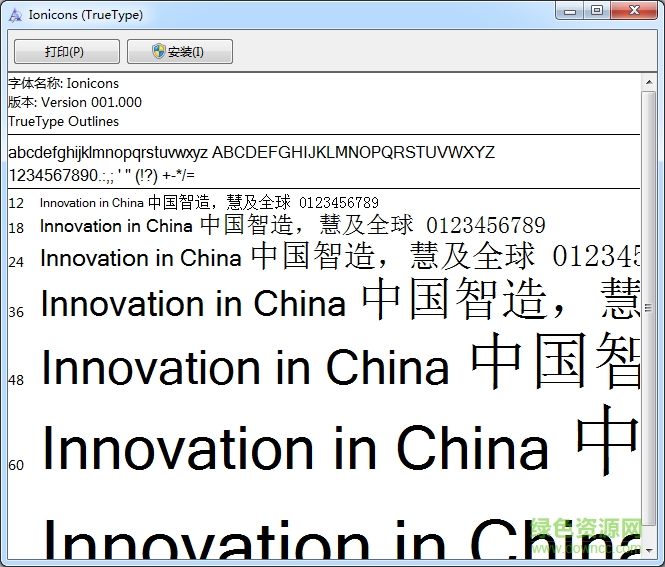
ionicons.ttf是系統(tǒng)軟件默認的一款字體,字形干凈簡練,有著端正的造型和大方的格調,常見iview等軟件中,若你的系統(tǒng)提示ionicons.ttf找不到或ionicons.ttf404,來綠色資源網重新下載即可!
ionicons字體作為系統(tǒng)中必備的ttf文件,在顯示圖片logo內容上很有自己的特色,無論是中文漢字和英文字體都很端正嚴禁,給人一絲不茍的視覺體驗,閱讀起來也顯得清晰明了!